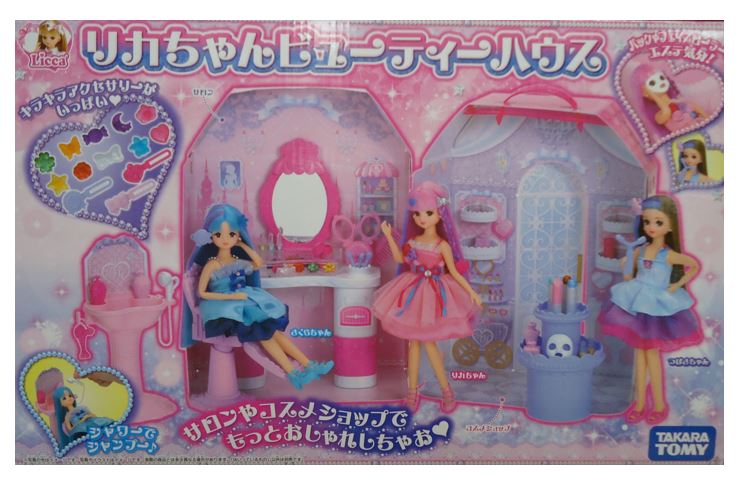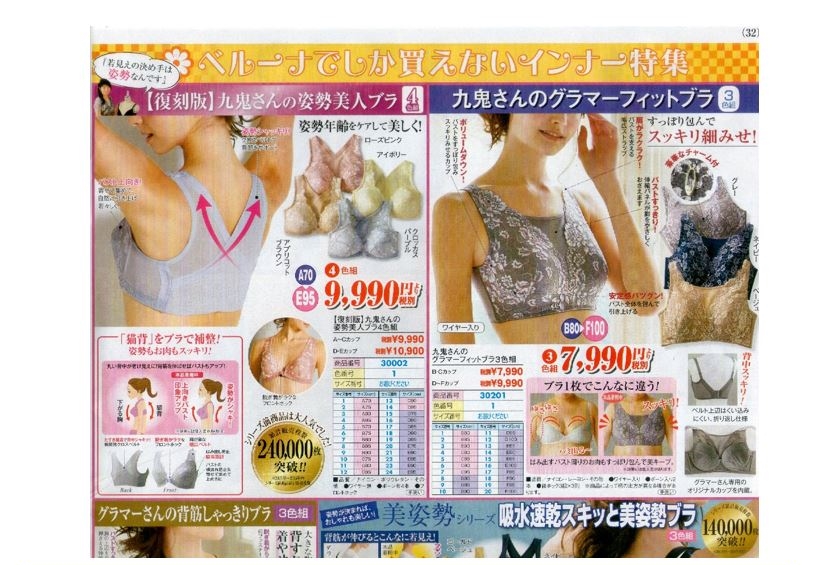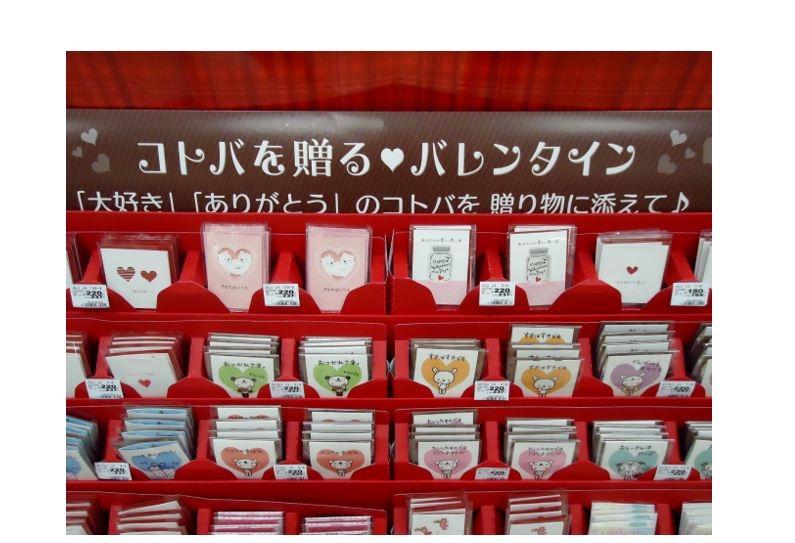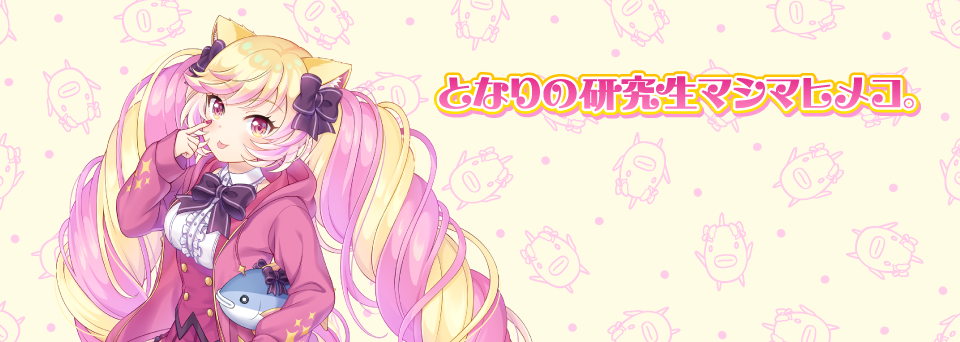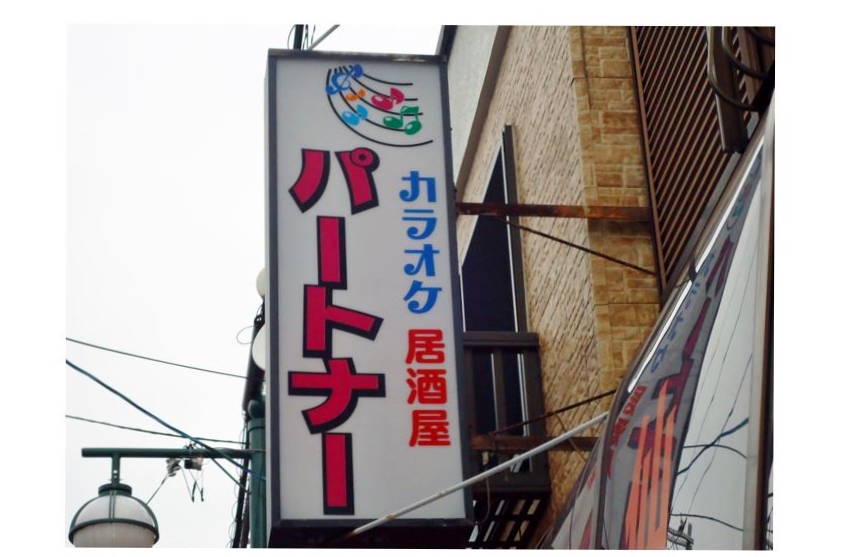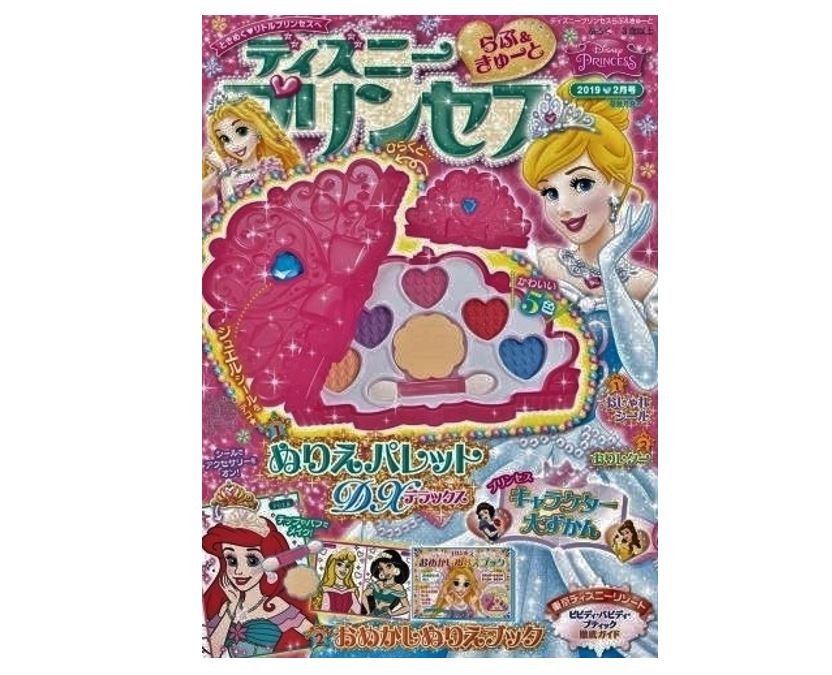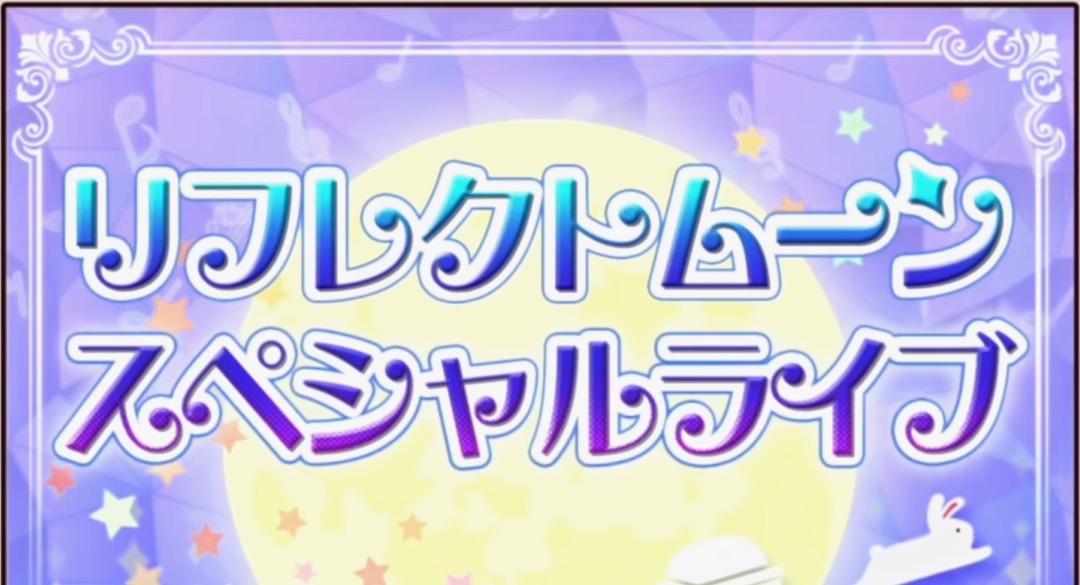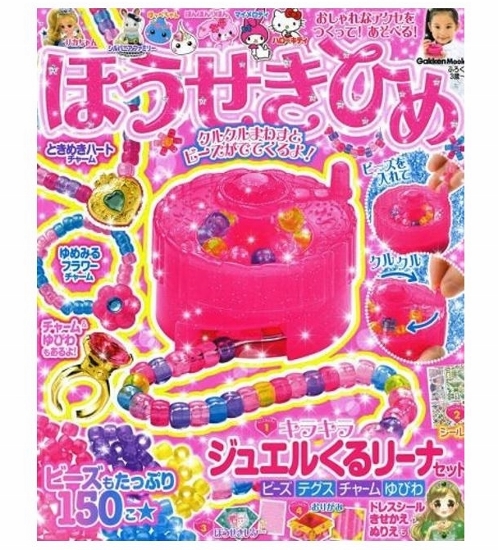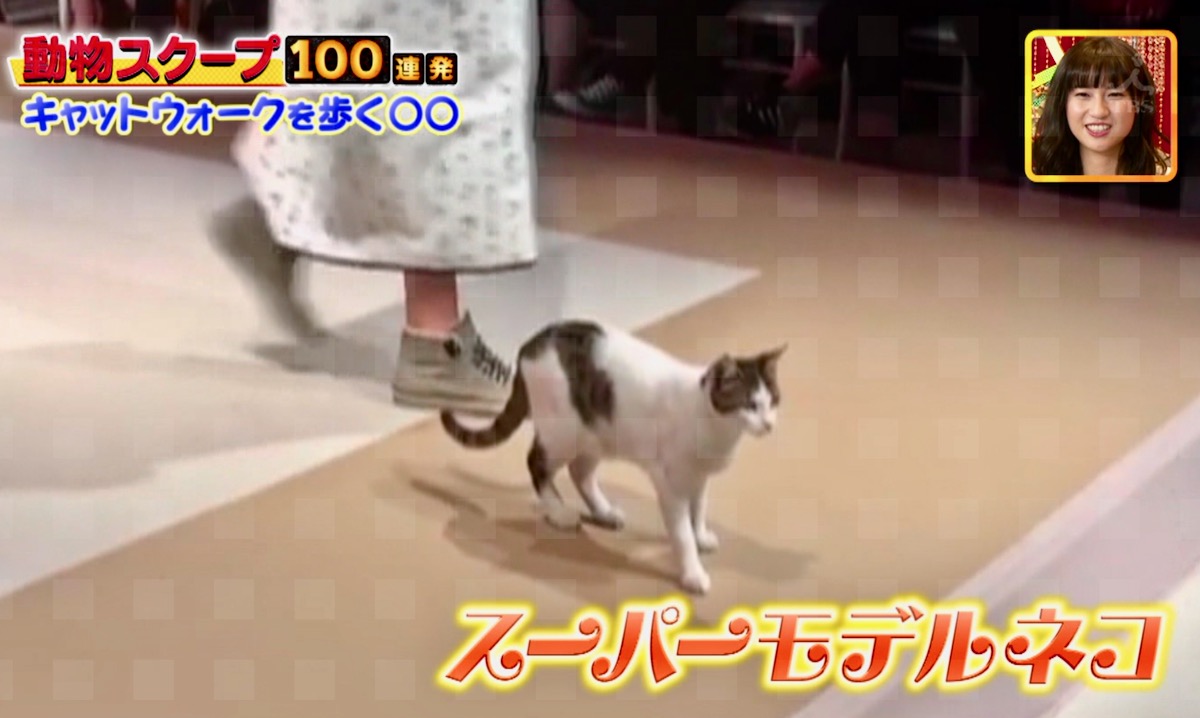
本の表紙 さとうゆたか
書名:トリックアートハロウィーン
著者:北岡明佳、グループ・コロンブス
発行:あかね書房
店名ロゴ さとうゆたか
西新井のショッピングモール内にあったタピオカ屋さん。
映画のエンデイング さとうゆたか
プリキュアオールスターズのエンディングタイトル。
YouTuberのブログ さとうゆたか
ラファエルの日々有給。
サインボード さとうゆたか
浜名湖、舘山寺付近。
クレープ さとうゆたか
某動物園売店のPOP。
MOOK表紙 さとうゆたか
書名:きせかえマグネットえほん
シリーズ:スター☆トゥインクルプリキュア
発行:講談社
本の表紙 さとうゆたか
書名:うちのカレー
著者:山口恵以子
発行:角川春樹事務所
テレビ番組 さとうゆたか
日テレの「メレンゲの気持ち」。
GYAOの番組 さとうゆたか
木村さ〜〜ん! | 無料動画GYAO!
「ピ」の半濁点の位置が変。無料のお試し版フォントのようだ(笑)。